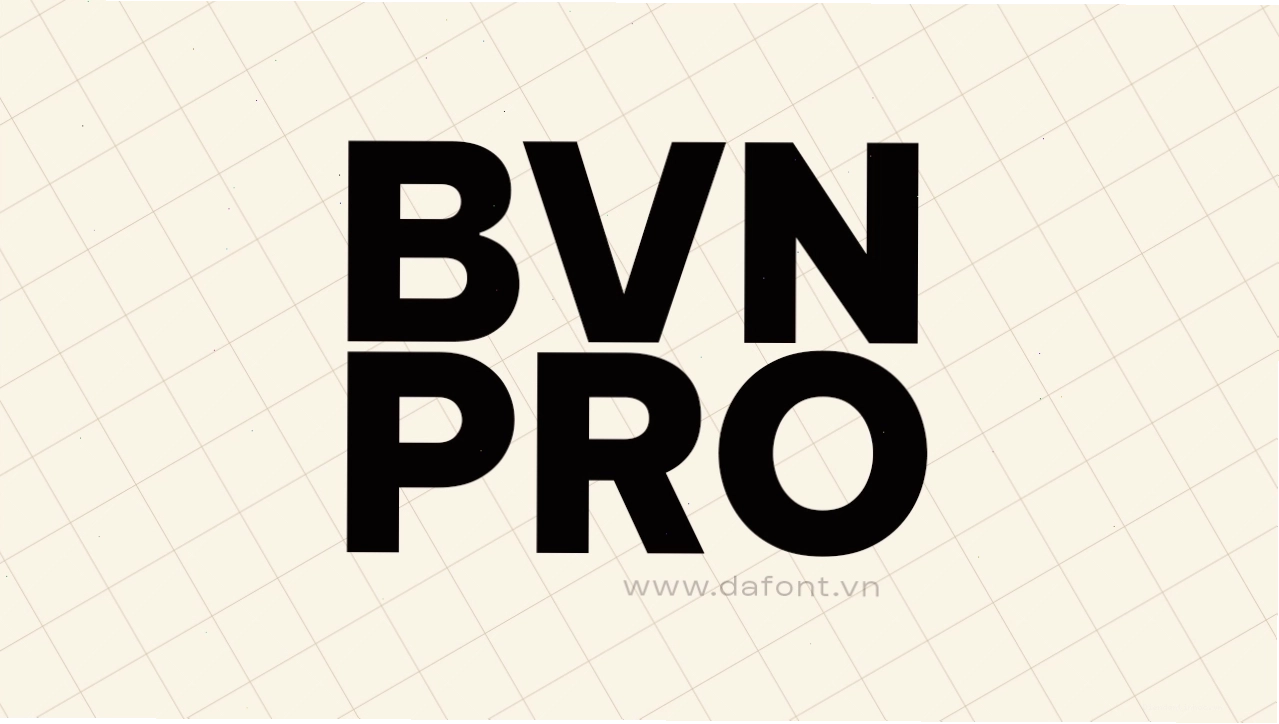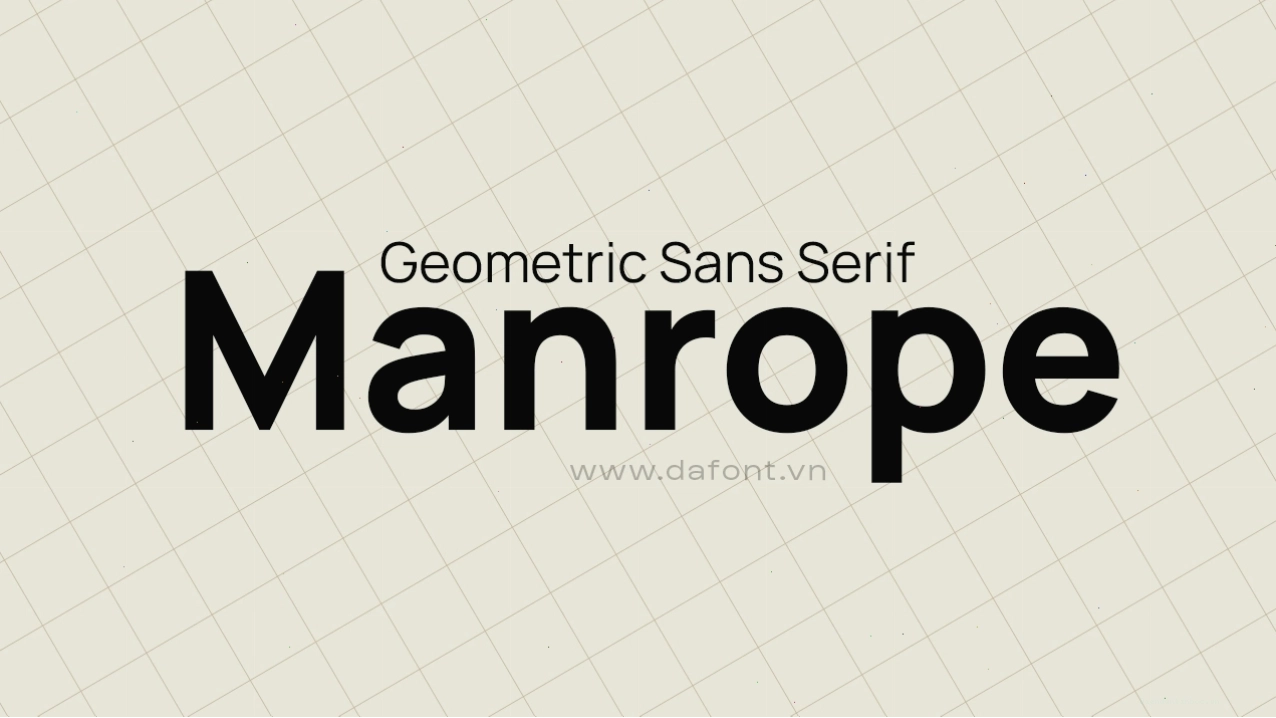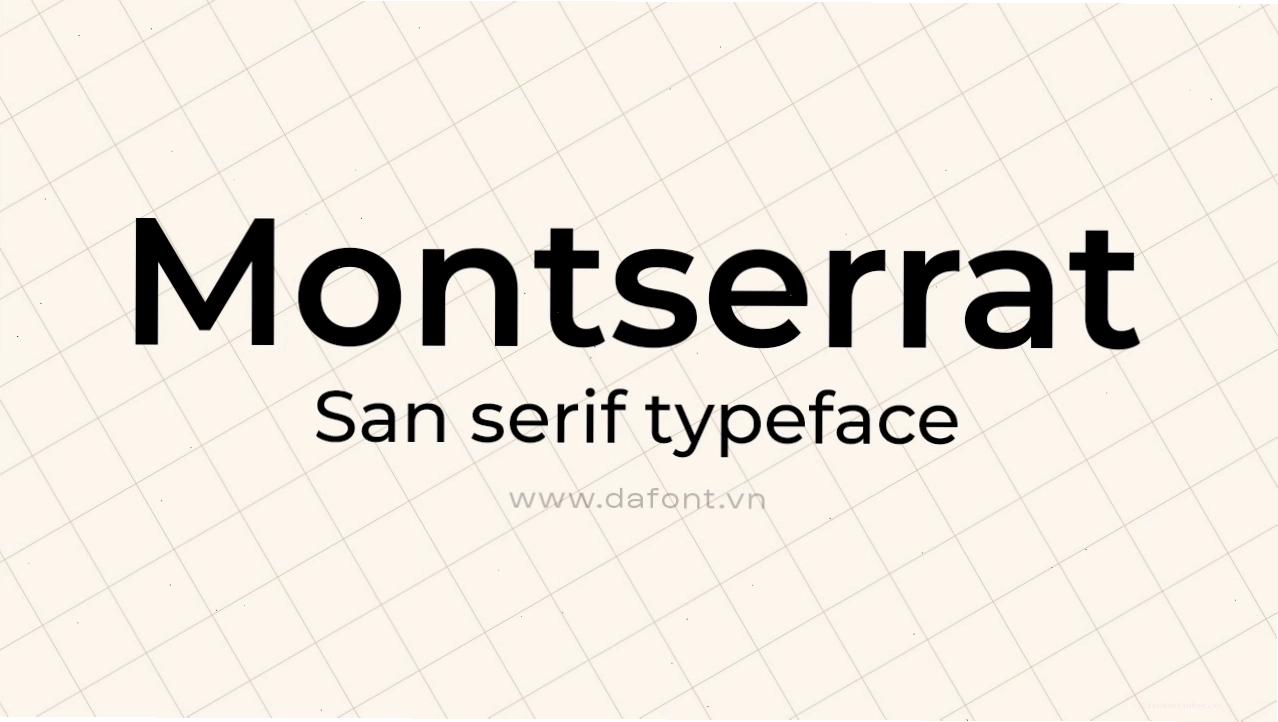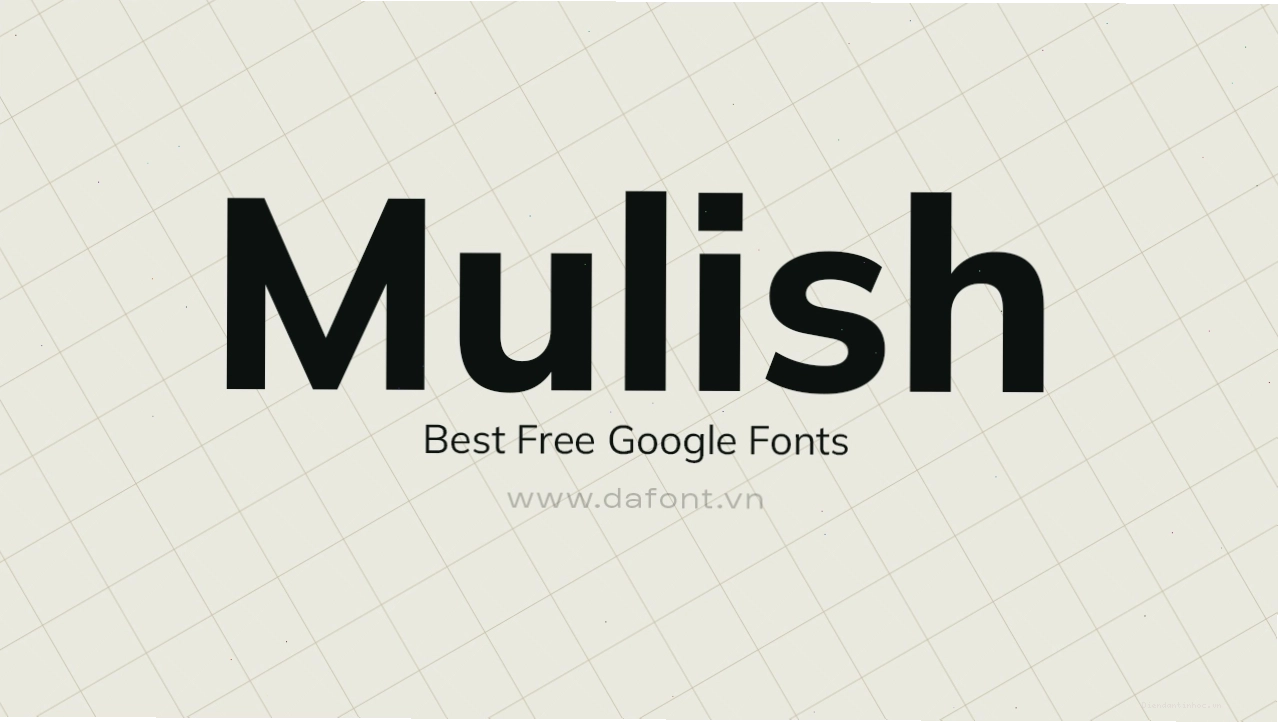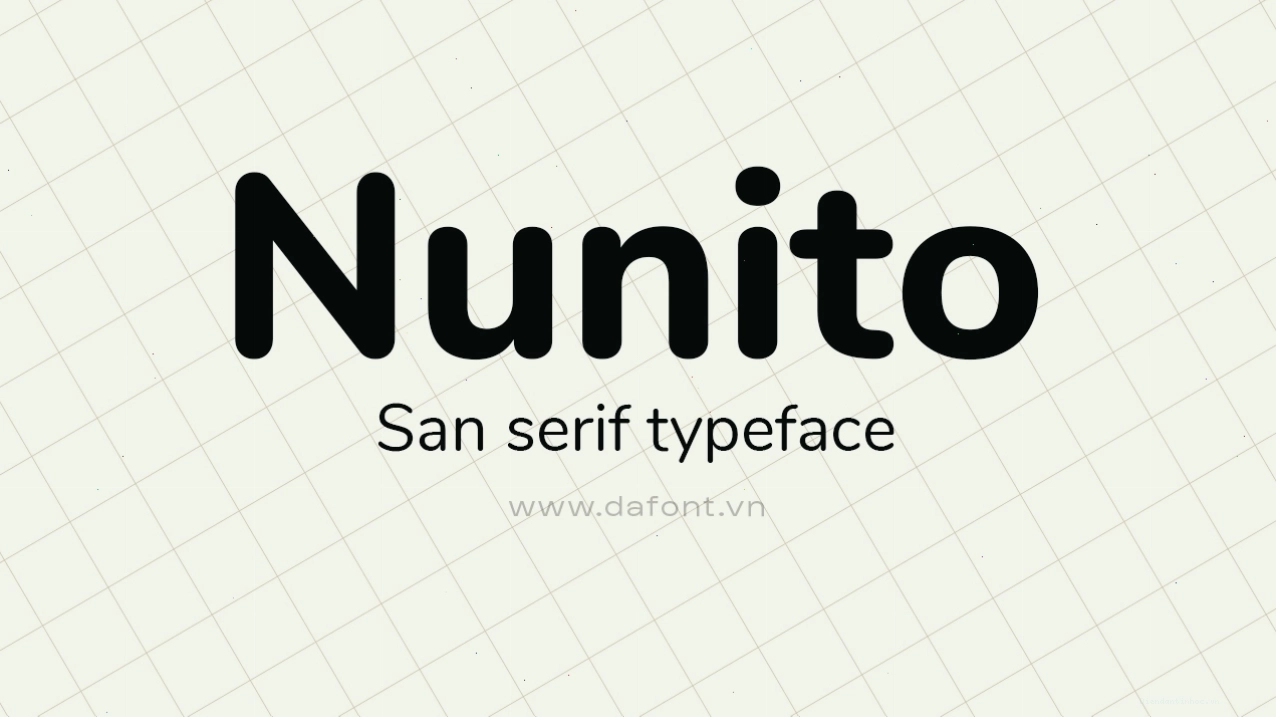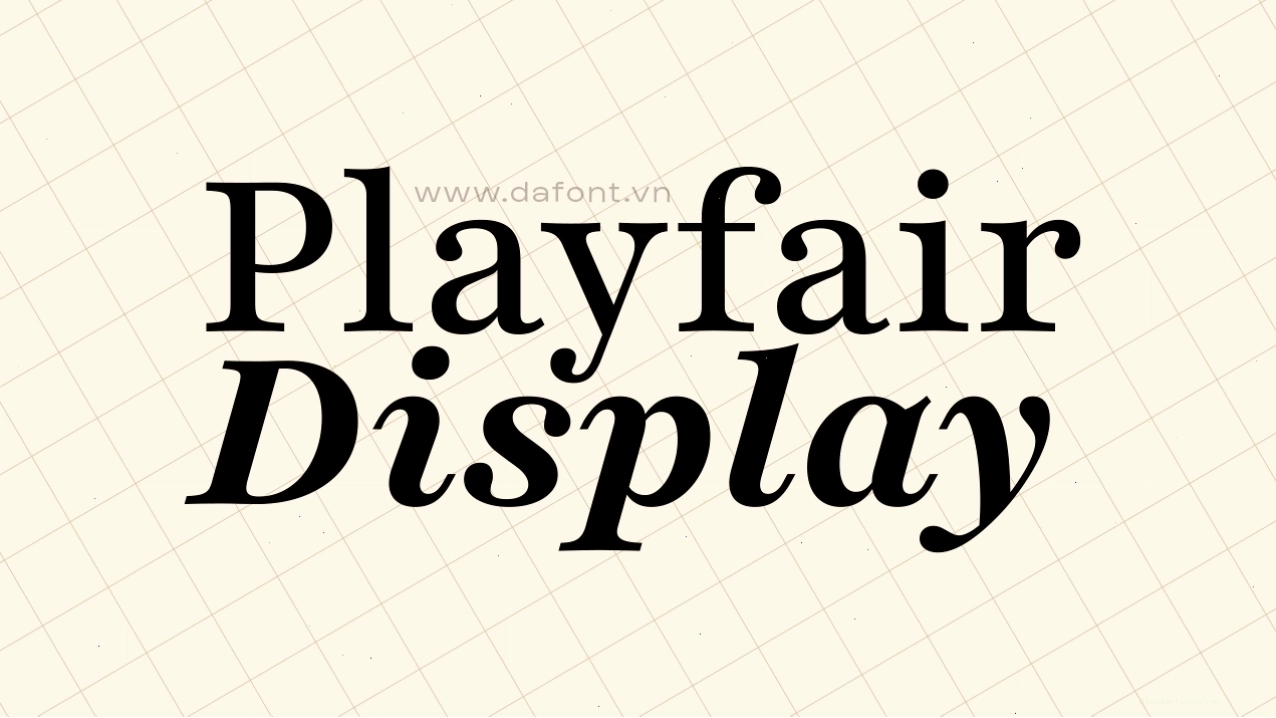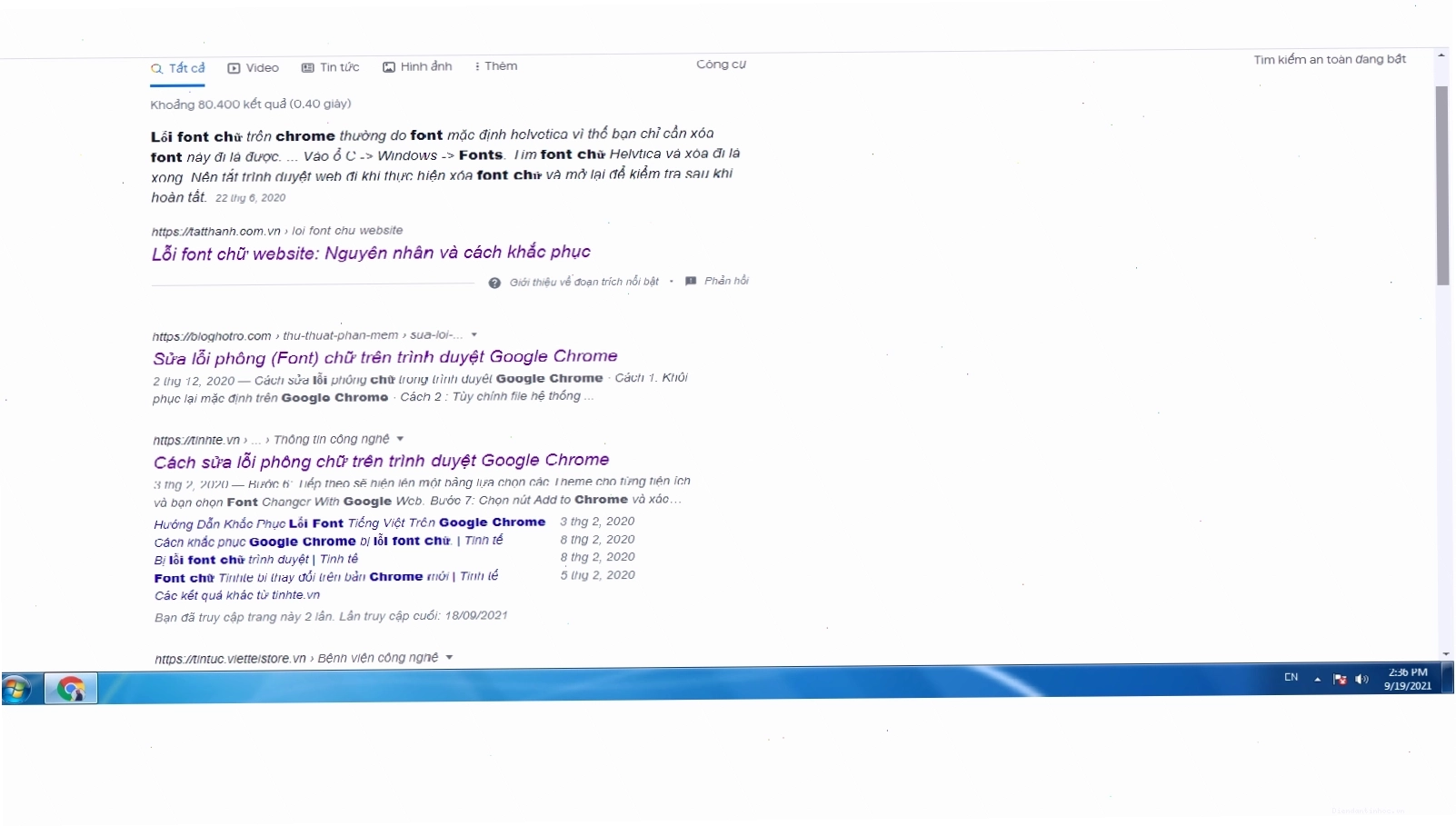
Khắc phục lỗi font chữ GG Chrome và khám phá Google Fonts tiếng Việt
Vấn đề: Lỗi font chữ trên các ứng dụng Google như Docs, Sheets, Tìm kiếm Chrome, ảnh hưởng đến trải nghiệm người dùng.
Giải pháp: Tải lại và cài đặt font chữ bị thiếu hoặc bị lỗi. Khám phá thư viện Google Fonts phong phú với nhiều font tiếng Việt đẹp mắt.
Lợi ích: Khắc phục sự cố hiển thị, cải thiện giao diện văn bản trên mọi nền tảng kỹ thuật số.
Hiểu rõ vấn đề lỗi font chữ trên Google Chrome
Tình trạng lỗi font chữ, đặc biệt là trên trình duyệt Google Chrome và các ứng dụng liên quan như Google Docs, Google Sheets, có thể xuất phát từ nhiều nguyên nhân khác nhau. Trường hợp phổ biến là do người dùng vô tình xóa nhầm các tệp font hệ thống hoặc font cài đặt trên máy. Khi các font chữ cần thiết để hiển thị văn bản bị thiếu hoặc hỏng, trình duyệt hoặc ứng dụng sẽ không thể giải mã và hiển thị ký tự một cách chính xác, dẫn đến tình trạng font bị lỗi, hiển thị ký tự lạ hoặc sắp xếp sai lệch.
Các trang web thông thường đôi khi vẫn hiển thị bình thường vì chúng có thể sử dụng các font chữ được nhúng trực tiếp hoặc các font hệ thống phổ biến khác. Tuy nhiên, các ứng dụng của Google thường có xu hướng ưu tiên sử dụng các font chữ đã được cài đặt sẵn trên hệ điều hành hoặc các font từ thư viện của Google. Do đó, khi các font này gặp sự cố, vấn đề lỗi font sẽ biểu hiện rõ rệt.
Minh họa lỗi font chữ trên Google Chrome và các ứng dụng Google
Hình ảnh minh họa cho thấy sự khác biệt trong hiển thị font chữ khi gặp lỗi.
Nguyên nhân và cách khắc phục lỗi font chữ trên Chrome
Nguyên nhân chính dẫn đến lỗi font chữ trên Google Chrome thường liên quan đến việc quản lý font trên hệ điều hành. Khi các tệp font hệ thống bị hỏng hoặc bị xóa, Windows hoặc macOS sẽ gặp khó khăn trong việc hiển thị văn bản một cách chính xác.
Tải lại và cài đặt font chữ cần thiết
Trong trường hợp bạn không chắc chắn font nào bị lỗi, việc khôi phục các font hệ thống mặc định của Windows hoặc macOS có thể là một giải pháp. Tuy nhiên, một cách tiếp cận chuyên nghiệp hơn là sử dụng các font chữ chất lượng cao, đã được tối ưu hóa và hỗ trợ tốt cho tiếng Việt. Đây là lúc Google Fonts phát huy vai trò của mình.
Tận dụng Google Fonts để giải quyết vấn đề font
Google Fonts là một thư viện khổng lồ cung cấp hàng ngàn font chữ miễn phí, chất lượng cao, được cấp phép theo Giấy phép Font mở (Open Font License). Điều này có nghĩa là bạn có thể sử dụng chúng cho cả mục đích cá nhân lẫn thương mại mà không phải lo lắng về vấn đề bản quyền. Google Fonts không chỉ cung cấp các font chữ đẹp mắt mà còn hỗ trợ đầy đủ các ký tự tiếng Việt, bao gồm cả các dấu thanh và chữ cái đặc biệt.
Việc cài đặt và sử dụng gg font tiếng việt từ thư viện này không chỉ giúp khắc phục lỗi hiển thị mà còn nâng cao đáng kể tính thẩm mỹ cho nội dung văn bản của bạn. Các nhà thiết kế, nhà phát triển web và người dùng thông thường đều có thể tìm thấy những lựa chọn phù hợp với nhu cầu của mình.
Khám phá các bộ font tiếng Việt nổi bật trên Google Fonts
Thư viện Google Fonts ngày càng phong phú với sự đóng góp của nhiều nhà thiết kế tài năng. Đặc biệt, có rất nhiều bộ font được Việt hóa hoặc thiết kế riêng để hỗ trợ tốt nhất cho ngôn ngữ tiếng Việt, mang đến sự đa dạng và cá tính cho mọi dự án.
Montserrat
Montserrat là một font chữ sans-serif hiện đại, được thiết kế bởi Julieta Ulanovsky. Lấy cảm hứng từ các bảng hiệu quảng cáo cổ điển tại khu phố Montserrat, Buenos Aires, font chữ này mang đến sự cân bằng hoàn hảo giữa nét đẹp truyền thống và tính thẩm mỹ đương đại. Với 18 biến thể font, Montserrat là một trong những bộ font chữ được yêu thích nhất trên Google Fonts, phù hợp cho cả tiêu đề và nội dung. Tải về Montserrat.
Font tiếng việt Montserrat với thiết kế hiện đại và đa dạng biến thể
Font Montserrat thể hiện sự hiện đại, dễ đọc và phù hợp với nhiều phong cách thiết kế.
Nunito và Nunito Sans
Nunito là một bộ font chữ sans-serif với các góc bo tròn mềm mại, tạo cảm giác thân thiện và dễ chịu khi đọc. Được tạo ra bởi Vernon Adams, phiên bản gốc có thiết kế khá độc đáo. Sau đó, Jacques Le Bailly đã phát triển thêm Nunito Sans, cung cấp một bộ trọng lượng đầy đủ hơn và phiên bản không bo tròn, mở rộng khả năng ứng dụng của bộ font này. Cả hai phiên bản đều hỗ trợ tốt tiếng Việt và thường được sử dụng cho các giao diện người dùng, nội dung web và in ấn.
Font tiếng việt Nunito và Nunito Sans với các đường nét bo tròn thân thiện
Nunito Sans mang đến sự rõ ràng, trong trẻo và dễ đọc, rất thích hợp cho nội dung dài.
Playfair Display
Playfair là một font chữ serif mang đậm phong cách của các kiểu chữ thế kỷ 18, thời kỳ Khai sáng châu Âu. Được thiết kế bởi Claus Eggers Sørensen, nó tái hiện lại sự tương phản cao giữa nét dày và nét mảnh, đặc trưng của các bản in thời kỳ này. Playfair Display rất phù hợp để sử dụng cho các tiêu đề, tên thương hiệu hoặc những đoạn văn bản cần tạo điểm nhấn sang trọng và cổ điển. Mặc dù là font serif, nó vẫn có thể được Việt hóa tốt và mang lại hiệu quả thẩm mỹ cao.